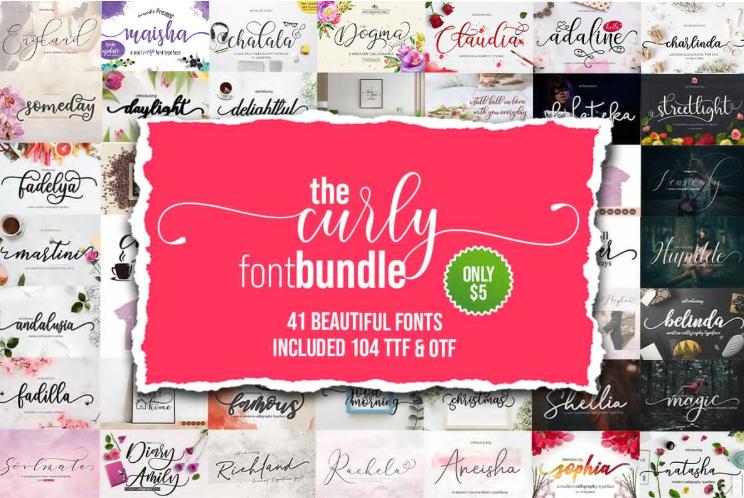
Набор шрифтов с завитушками.
В этом наборе 41 вид шрифтов, которые удовлетворят все ваши потребности в рукоделии!
Большинство из этих шрифтов имеют PUA-код, что означает, что они содержат прекрасные дополнительные символы.